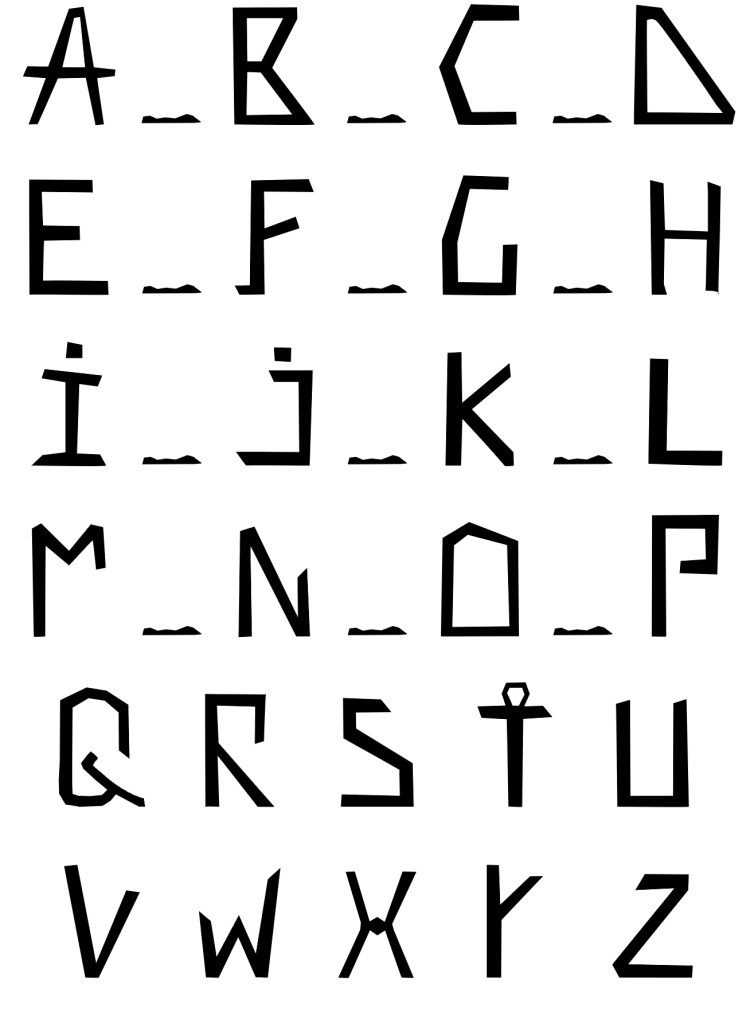
1 L’alphabet par le peuple et pour le peuple
Au fait ! En quoi est-ce intéressant ?
Après tout, l’alphabet est une suite graphique aussi connue et banalisée que le nom des couleurs ou la signalisation routière.
L’ordre alphabétique est une norme sévère, une loi incontestée. Nous utilisons d’ailleurs de terme « police » pour définir les caractéristiques graphiques d’une écriture.
Cette conformité ne nous empêche pas de créer chaque jour de nouvelles façons de calligraphier, discipline artistique majeure, pour nous en servir d’enluminures, logos et signes de reconnaissance.
Sensation unique, nous savons que notre mode d’expression est partagé par une bonne partie de la Planète. Des milliards d’êtres humains utilisent un alphabet, dont nous ne comprenons pourtant ni la langue ni même l’écriture.
En explorant ce que nous avons en commun, nous allons chercher la souche unique de tous les alphabets, l’équivalent du tronçon d’ADN culturel d’un très grand nombre.
Identifier les « Adam et Ève » de nos lettres nous permettra de connaître les racines partagées, nous aidera à affiner notre vision de certaines périodes de l’histoire et, pourquoi pas, nous facilitera la lecture des écritures parentes.
Construire Un Alphabet.
Voici une activité épanouissante qui va de l’amusement enfantin jusqu’au projet de cryptologie le plus complexe et réciproquement. Comme l’objet de notre quête est à l’origine assez ludique, nous allons nous amuser à pister les traces que nous ont laissées nos prédécesseurs, qui dessinaient d’élégantes volutes sur la pierre, le papyrus, le parchemin, la peau et le papier. Par exemple, l’alphabet Latin moderne de base, pour une police de caractères simple, sans effets, va se présenter de la façon suivante.
Ce Qui Fait un Alphabet
Ce n’est pas compliqué. C’est une liste de lettres qui sont utilisées afin d’assembler des objets que nous pouvons assez bien comprendre pour les lire, les parler ou les chanter. Il s’agit d’un moyen de communication artificiel complétant les moyens naturels
Nous comprenons qu’un alphabet est un code et que son objet principal est de fabriquer des messages. Il faut que l’émission et la réception se fassent sans dégradation des significations, ce qui implique que des critères logiques doivent être respectés.
Il est composé de signes distincts.
Ces signes sont en nombre limité.
La collection est définie et immuable, ou presque.
Les lettres sont accolées pour former des éléments prononçables, les syllabes.
Les syllabes sont assemblées afin de former des mots plus ou moins complexes.
On doit comprendre où commence et où s’arrête un mot.
Un même alphabet peut servir à l’expression de langages distincts.
C’est là que ce bel ordonnancement dérape, car si un alphabet sert de base commune à des langues différentes, chacune d’entre elle a ses propres besoins.
Pour respecter les prononciations il peut être nécessaire d’ajouter des caractères d’accentuations.
Si cela ne suffit pas, on ajoute des signes spécifiques.
Quand une langue le nécessite, elle utilise une lettre pour une autre ou crée ses propres signes.
Il ne s’agit pas de simples détails d’adaptation car à la fin, il est utile de connaître l’histoire d’une langue pour en comprendre l’alphabet, même si celui-ci provient de la même souche que la nôtre.